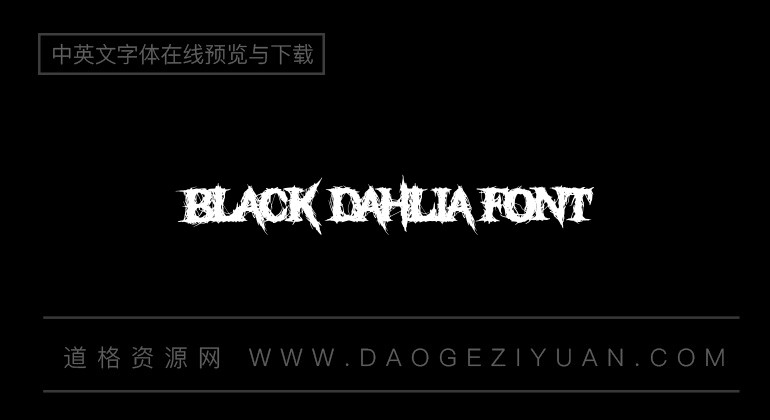
Black Dahlia Font
Black Dahlia Font 是一种艺术字体,通常用于设计、标题、海报和标志等领域。它的特点是字母笔画带有弯曲的线条和装饰性的元素,使得字体看起来非常华丽和独特。它的设计灵感来自于黑色大丽花(Black Dahlia),这是一种在20世纪40年代发生的著名谋杀案中的受害者名字。因此,这个字体通常被认为是具有一定的神秘和犯罪色彩的字体,适合用于特殊场合和具有冲击力的设计中。
Black Dahlia Font是一款非常不错的手写艺术字体,具有很好的视觉感,适合于文化类的宣传设计、商业类品牌的广告和产品包装设计以及个性化文字排版等较多场景。